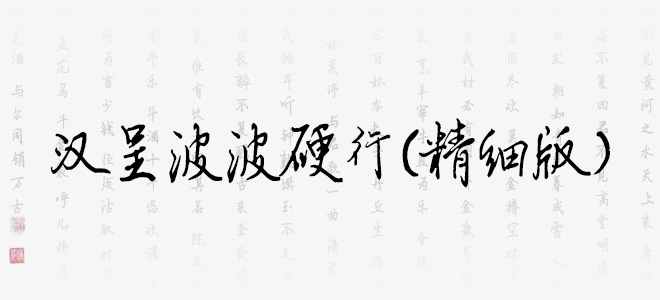
漢呈波波硬行(精細(xì)版)是一款非常蒼勁的手寫風(fēng)格藝術(shù)字體,字體線條粗細(xì)適中,筆畫隨性,結(jié)構(gòu)灑脫自在,具有很好的視覺(jué)感,適合于文化類的宣傳設(shè)計(jì)、商業(yè)類品牌的廣告和產(chǎn)品包裝設(shè)計(jì)以及個(gè)性化文字排版等較多場(chǎng)景。
漢呈波波硬行(精細(xì)版)